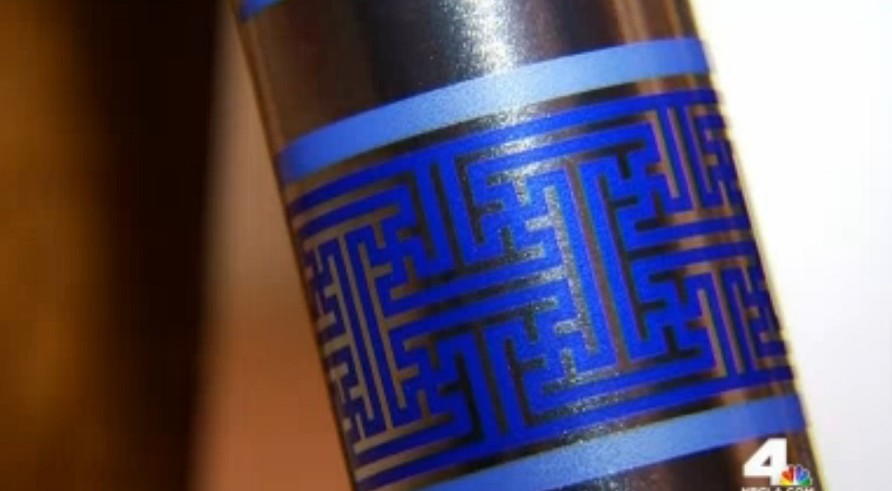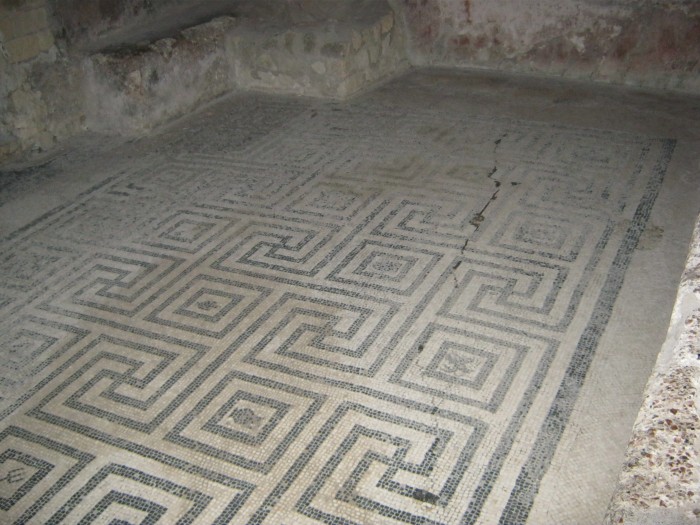
Das hat mich ja auch sehr beeindruckt. Ist so vielschichtig und hintergründig. Da hat sich jemand viele Gedanken gemacht.
Mit gutem Geschmack und gezieltem Einsatz kreativer Zeichensetzung ist eben selbst aus der guten alten CS noch mehr herauszuholen, als selbst die Profis gedacht hätten. :nicken:
Du hast die wesentlichen gestalterischen Eckpfeiler perfekt zusammengefaßt. Die Frage ist, ob man bei einem Redesign im Rhener Style nicht urheberrechtliche Grenzen touchieren würde.
Wenn die Gestaltung hier so gut ankommt, wäre sie vielleicht auch etwas für nächste Redesign. :party:
Bitte beschreit das nicht. Sonst kommt nach der Retro-Handmade-with-a-ballpen-Welle tatsächlich noch die Retro-Ugly-is-the-new-cool-Welle.
Eine amerikanische Drogeriekette hatte kürzlich dieses Einwickelpapier im Angebot:
Preisfrage: an welches Fest soll das abgebildete Muster erinnern?
Logisch: an das jüdische Chanukka-Fest! Logisch auch, dass der Skandal nicht lange auf sich warten ließ.
The Times of Israel berichtete, journalistisch sachlich. Bis zum vorletzten Satz. :party:
Ich fand auch den letzten Satz sehr sachlich.
Ich finde, man sollte aufhören, in jedem uralten Muster, in dem sich durch den verschlungenen Linienverlauf eine Form ergibt, dass man da ein Swastika heraus schnippeln kann in die Nähe mit denen zu bringen, welche dieses sonst weltweit bekannte Zeichen einst derb vergewaltigt haben. Ich glaube, das dort abgebildete Mäander-Muster in Mosaiken aus Babylon gesehen zu haben. Auch im römischen Reich waren solche Muster beliebt, Müssen wir jetzt in den Ruinen von Herculaneum jetzt auch die Hakenkreuze heraus meißeln?
Und was ist mit Finnland? Sind das alles Nazis, die da Militär-Flieger werden?
Ja, hab ich auch schon live gesehen, und zwar hier:
Ist tatsächlich in Herculaneum und scheinbar ein sehr populäres Motiv gewesen.
Trotzdem: Wenn man sich daran macht, ein Einwickelpapier fürs Chanukka-Fest zu entwickeln, sollte man lieber dreimal hinschauen, auf welche Weise man da jemandem auf den Schlips treten könnte. Schließlich werden die meisten Menschen die Swastika nicht mit Herculaneum oder Babylon in Verbindung bringen, sondern eben mit etwas anderem.
an diesem italian-design-schrottwerk ist das ornament im hintergrund aber nicht das schlimmste …